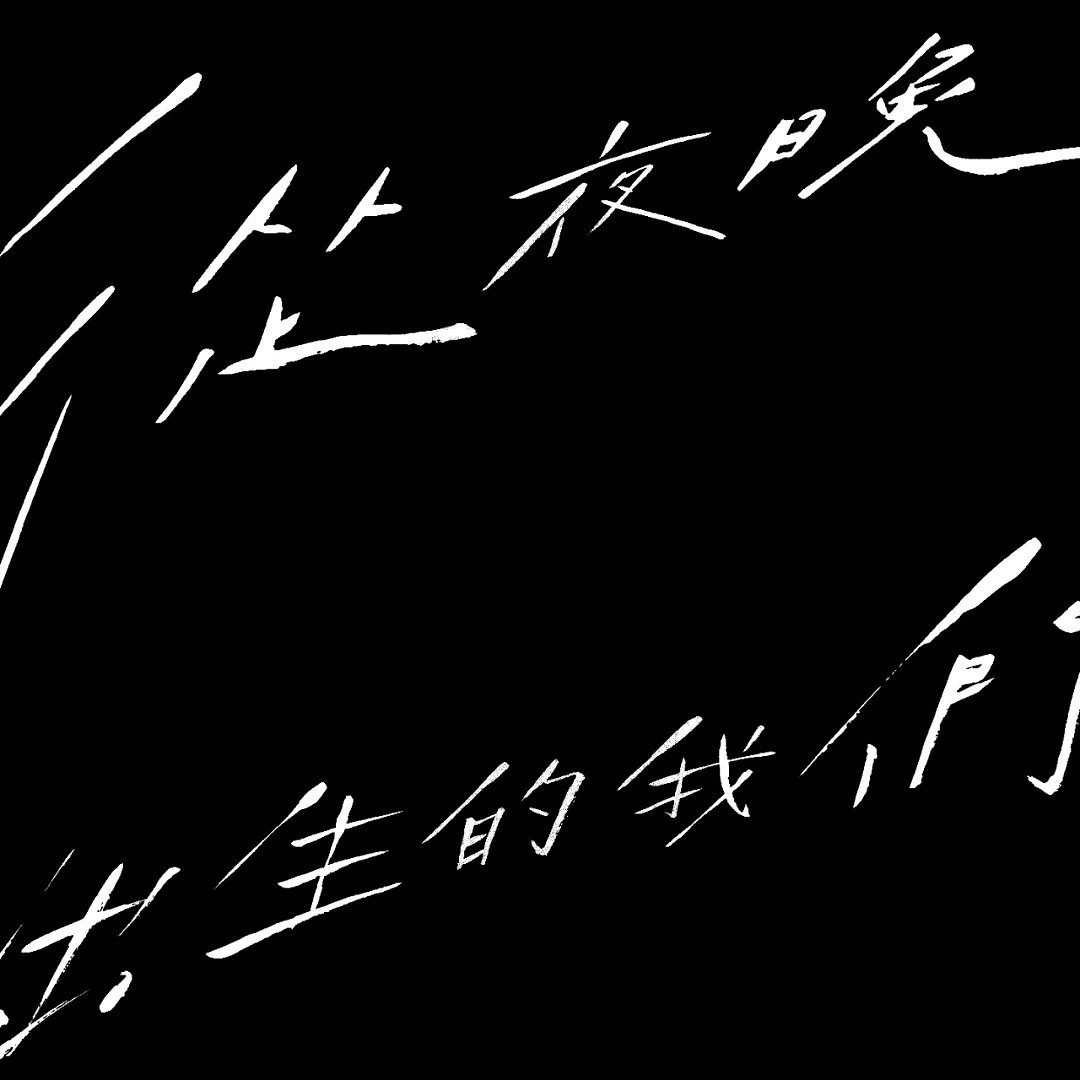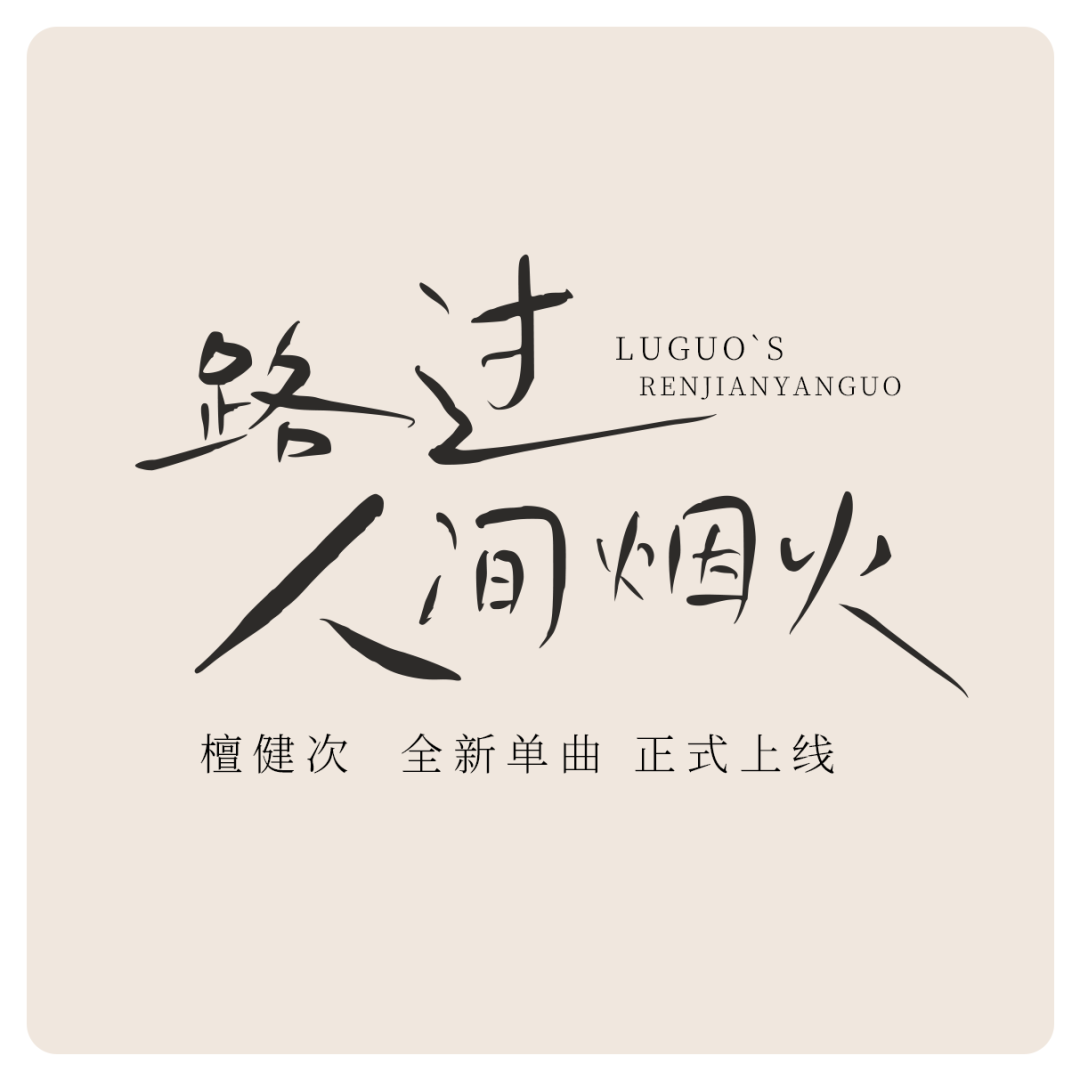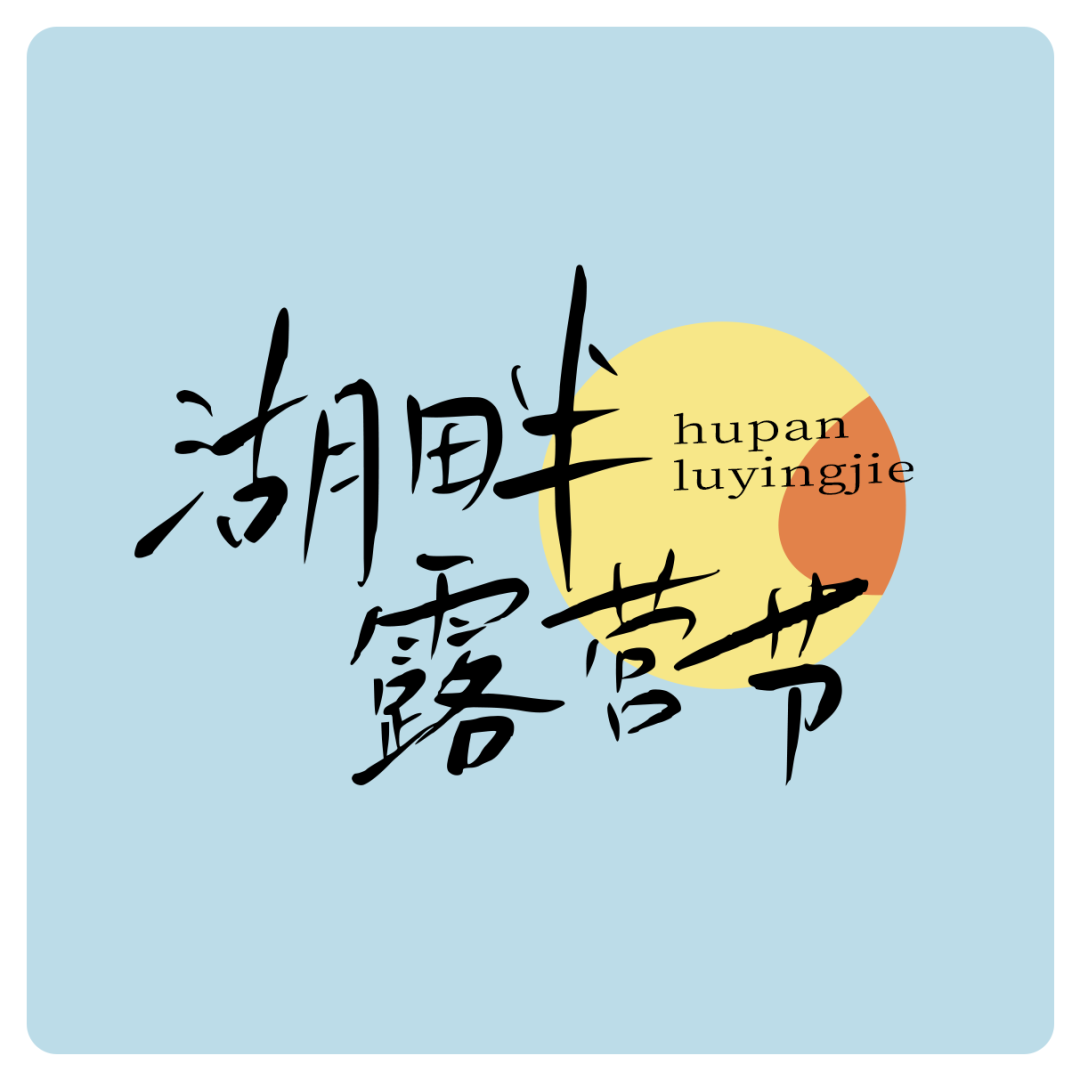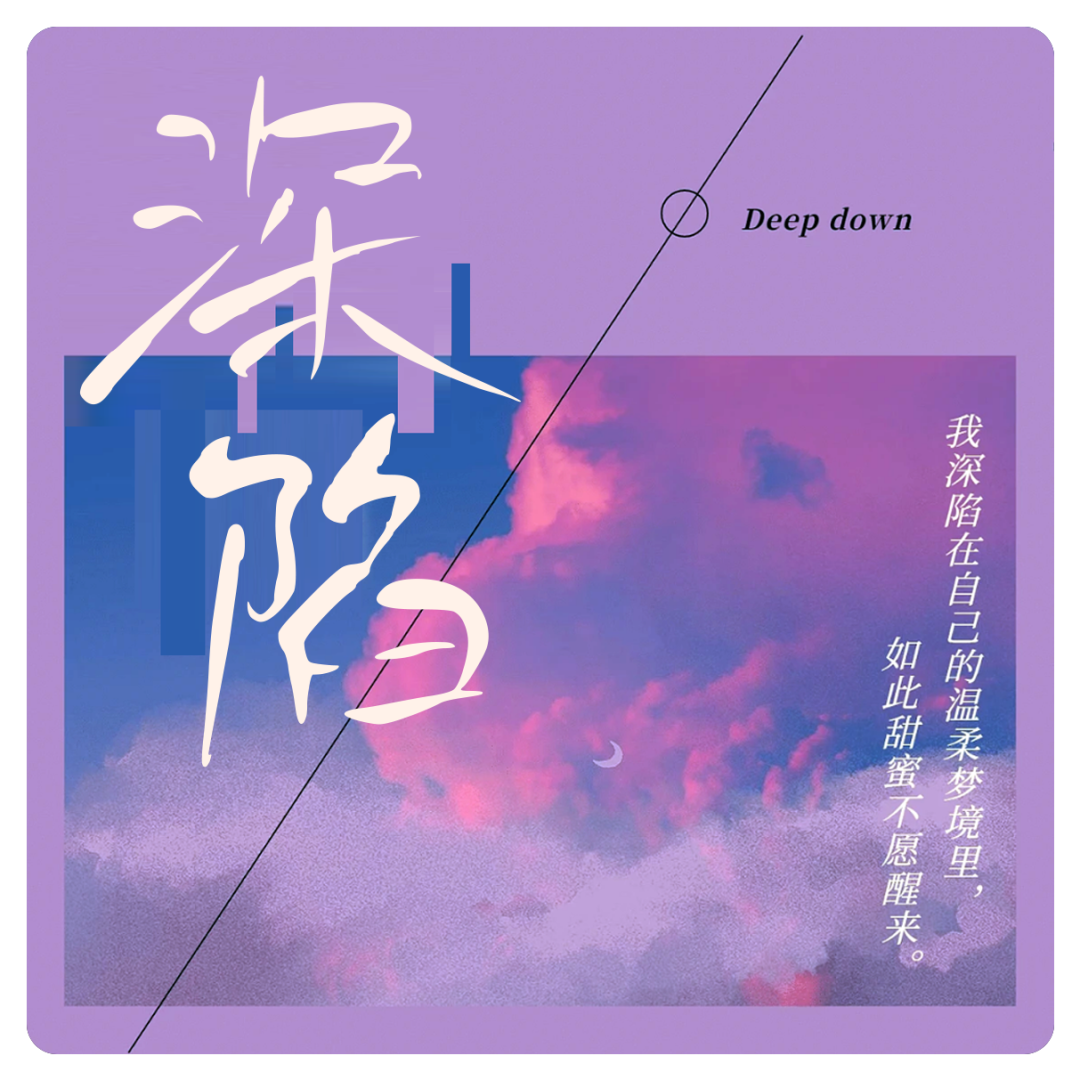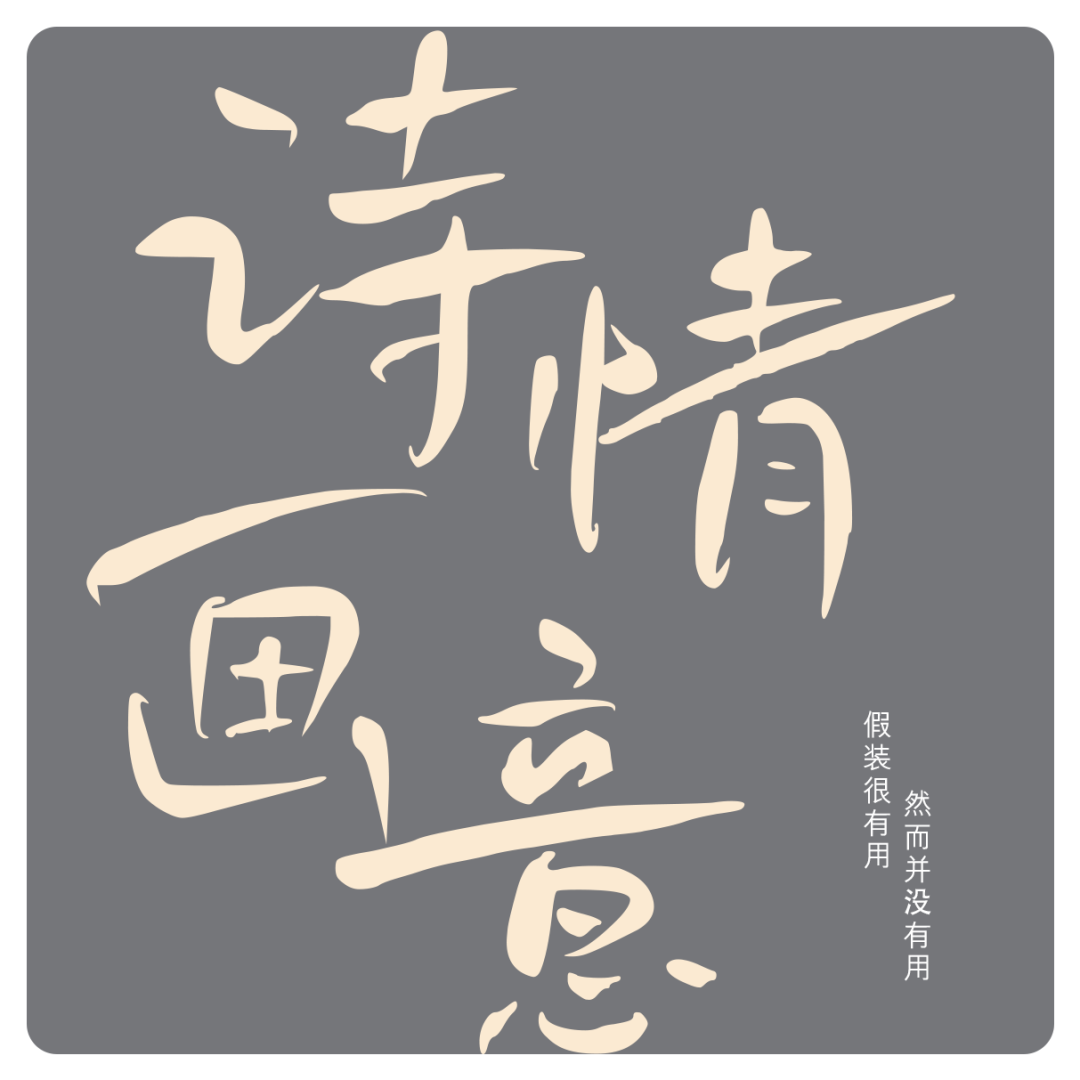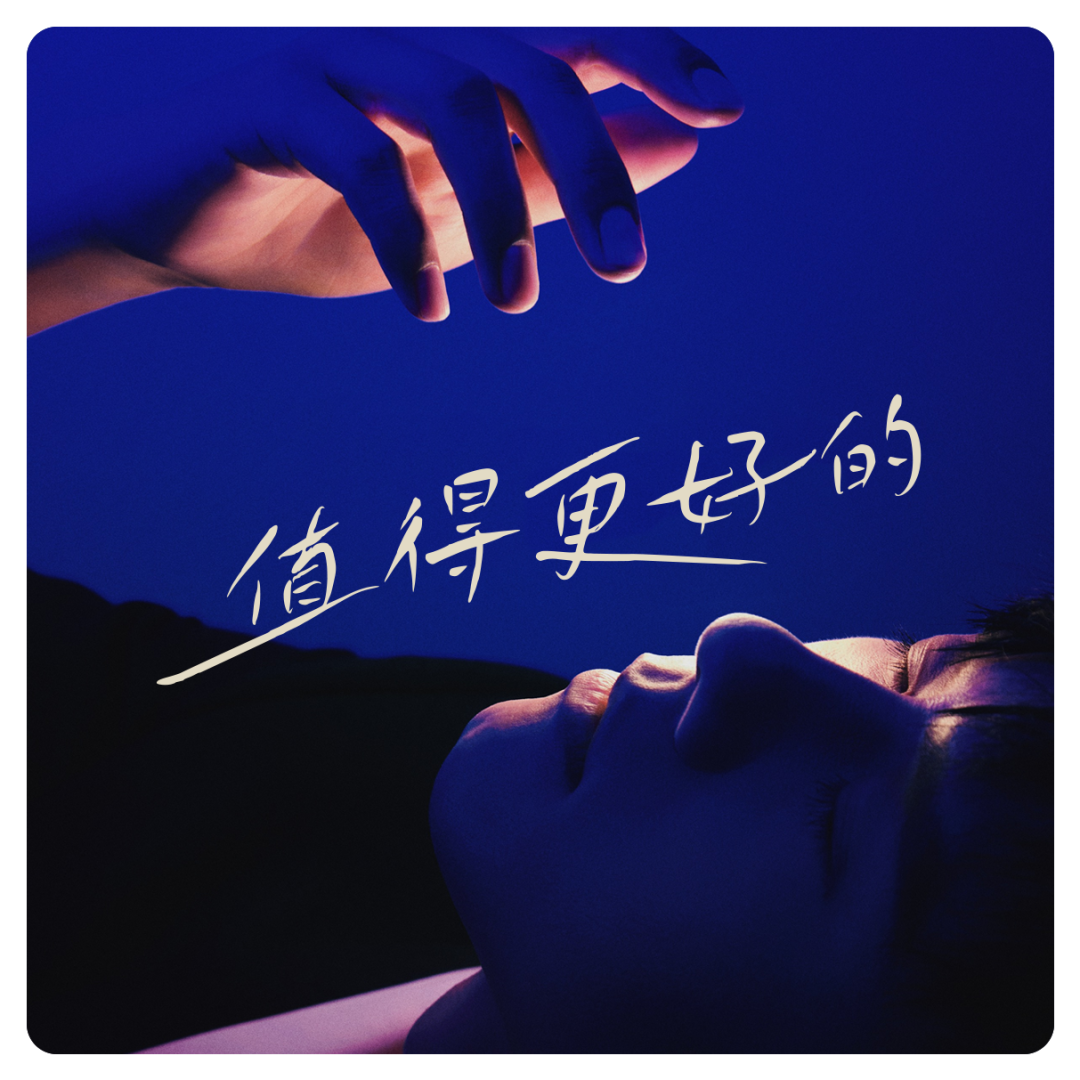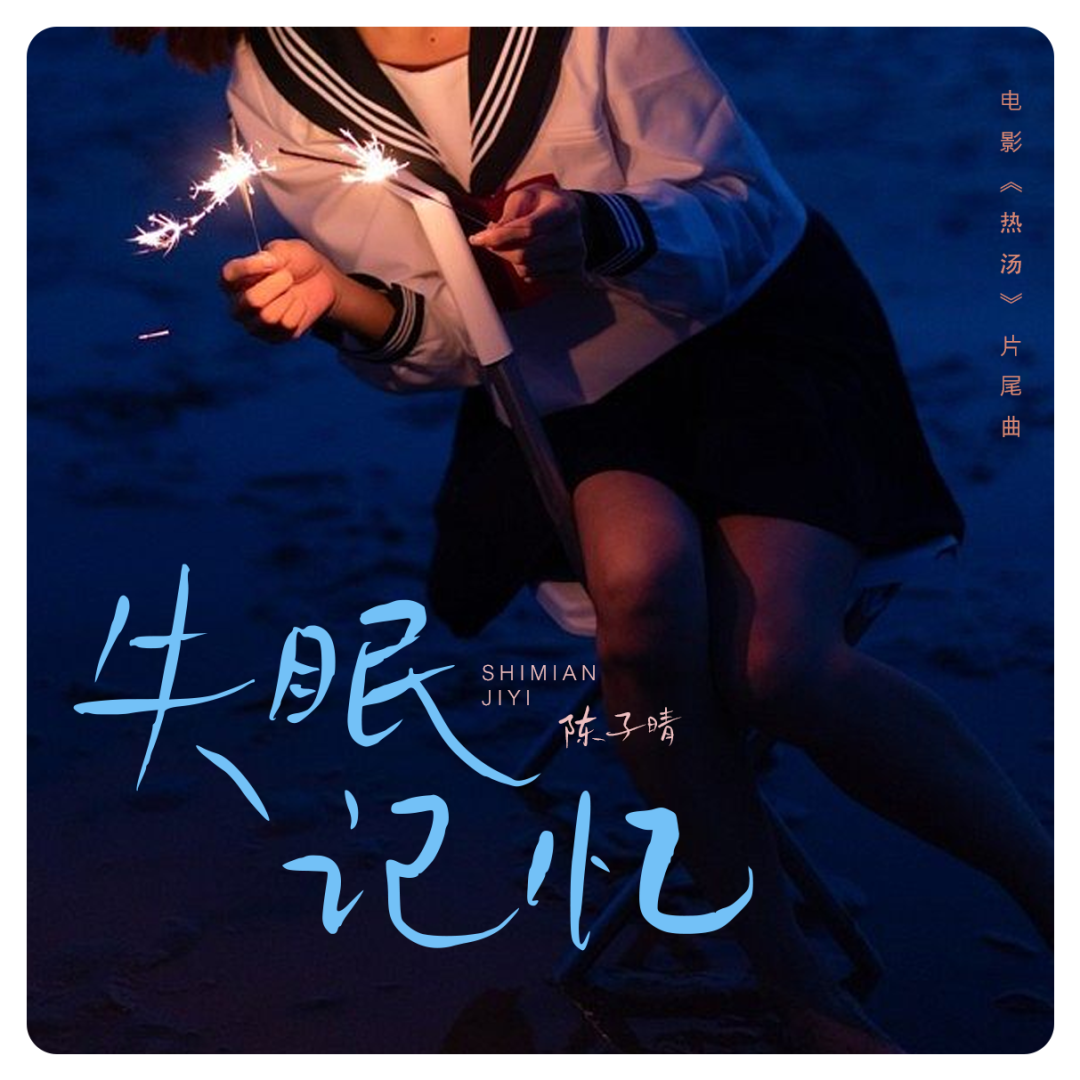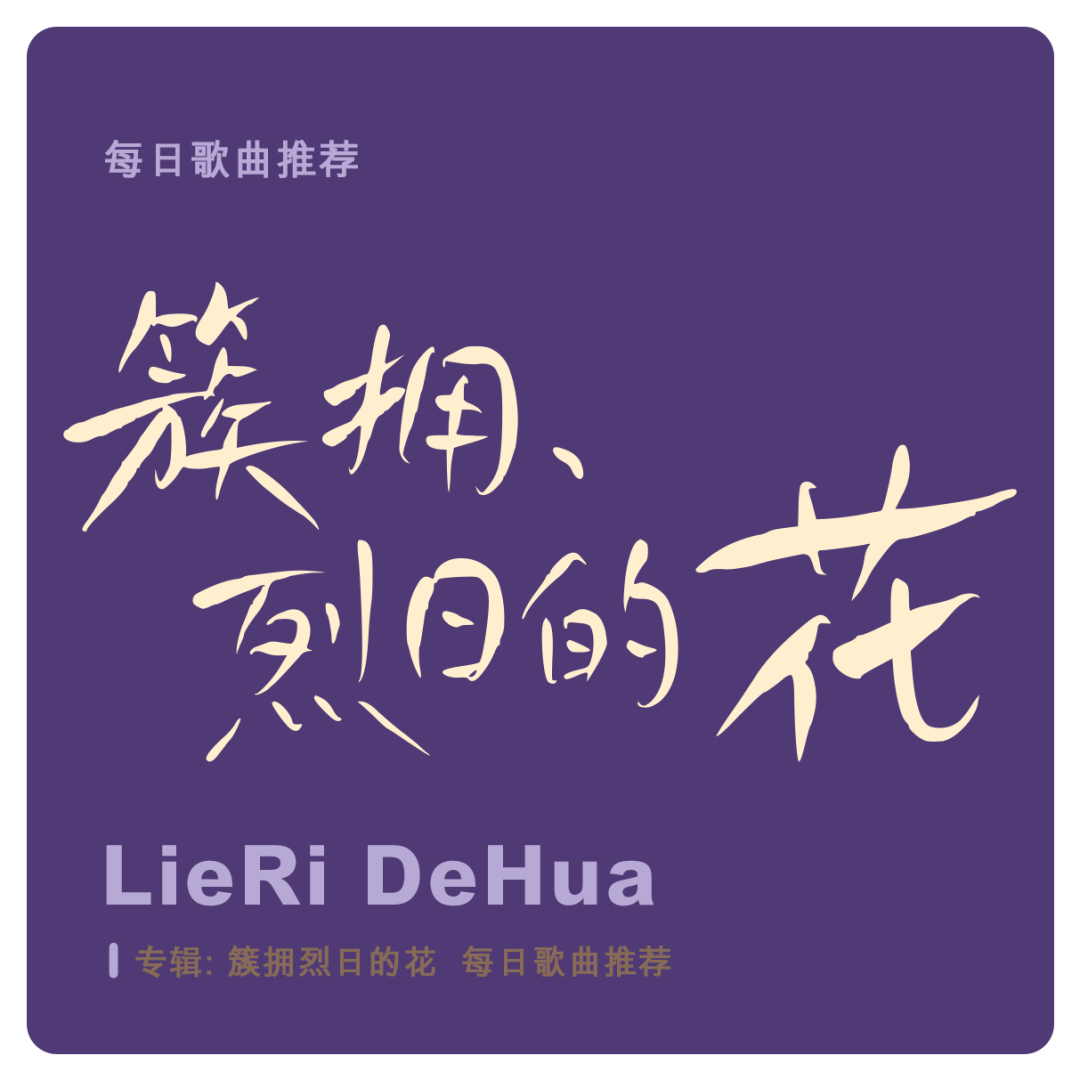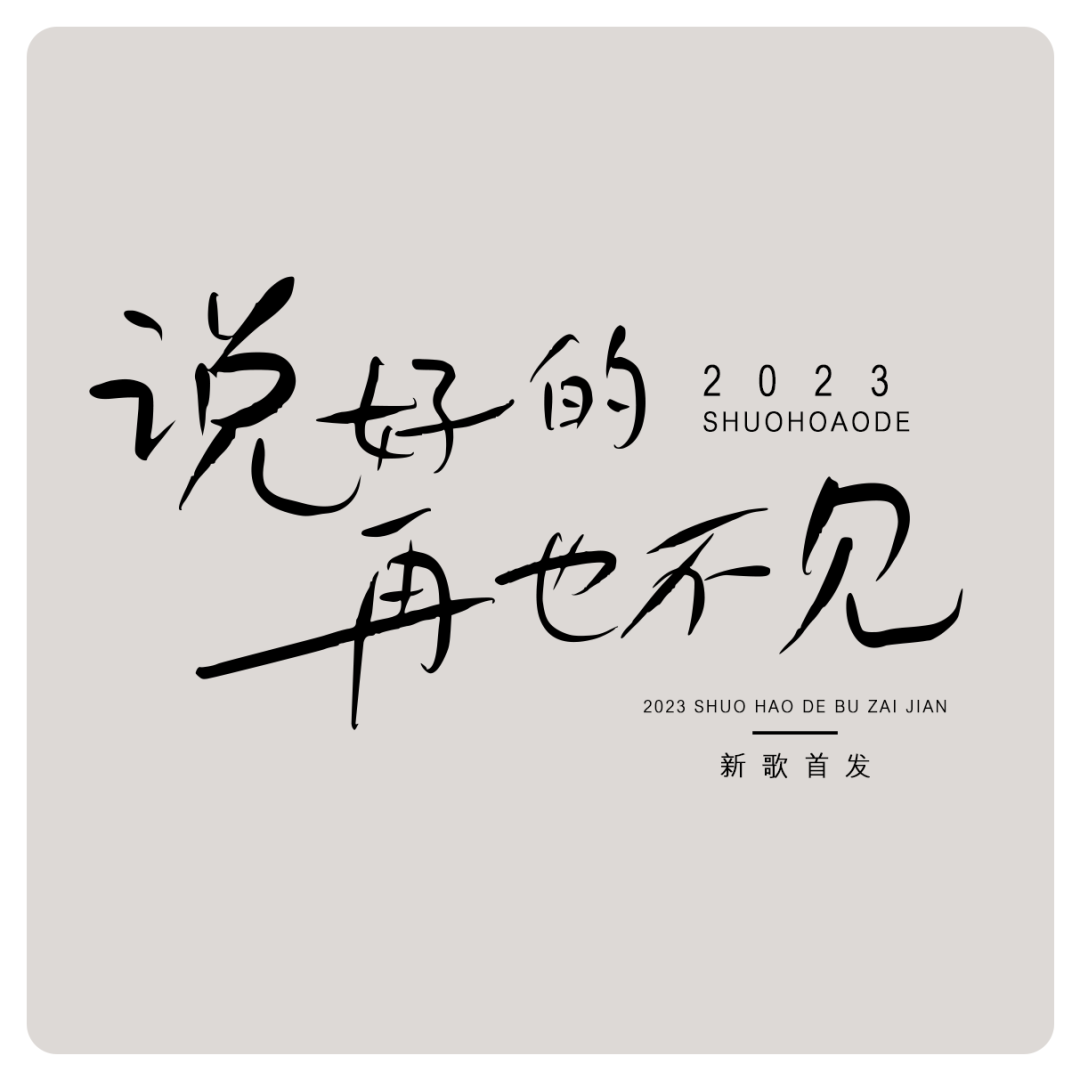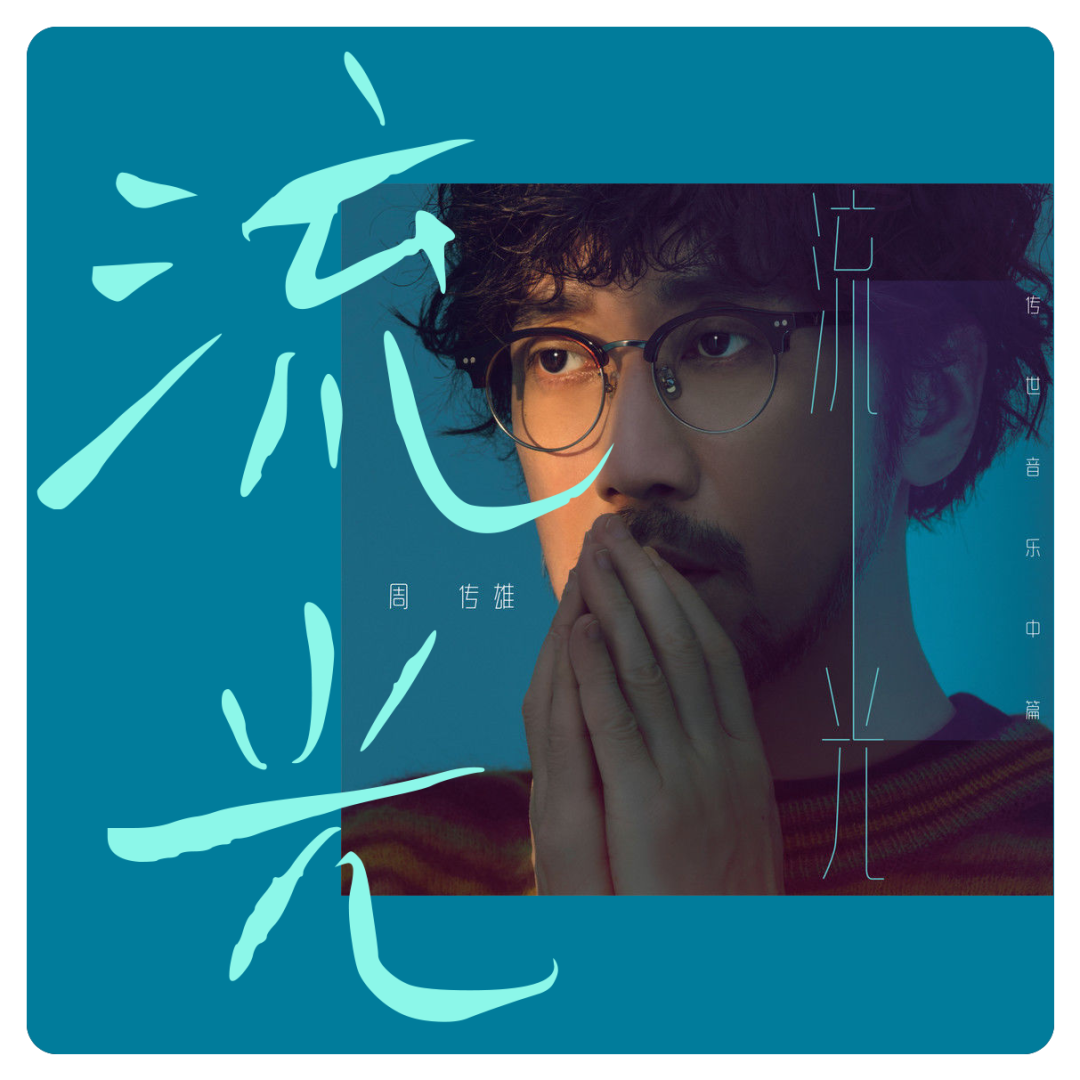
关于这套鸿雷拙书简体被我遗弃,又被我从回收站里捡回来的字体|再丑也有用武之地(免费商用)
关于这套被我从回收站捞起来的字体简单说两句
这套字体写于2021年6月份
命名为《鸿雷拙书简体》
拙的本意就是拙略,“丑”的意思,因为写完后才发现是真的丑,放在文件夹里一年半了,前几天整理文件的时候没有任何犹豫直接被我删了。
然而前几天有个客户发了几张图给我,问我海报上面的字体会写吗。